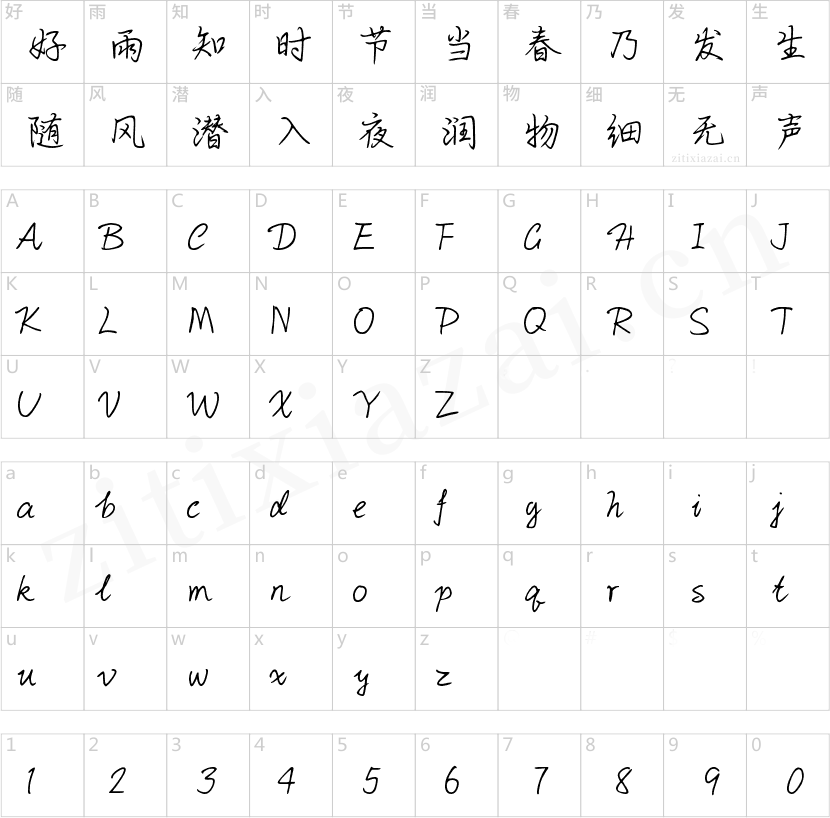
Aa做不到人人喜欢,这款字体结构工整、笔画清晰,兼顾美观与易读性,适用于标题、正文、海报、包装、LOGO 等多种场景。字形优雅稳定,风格百搭耐看,适配日常排版与创意设计,让文字呈现更舒适、更具质感。Aa做不到人人喜欢一笔一画,皆是细节,以均衡的比例、流畅的线条打造舒适视觉体验,字形端正大气,风格简约现代。无论是商业设计、品牌宣传还是日常排版,都能轻松驾驭,让文字更有格调与力量。Aa做不到人人喜欢字体下载。
Aa做不到人人喜欢是一款非常具有艺术性的字体,它的设计灵感来源于对古典艺术的研究,同时又融入了现代字体设计的元素。字形优美,笔画粗细变化自然,给人以大气、典雅的感觉。Aa做不到人人喜欢是一款既传统又现代的字体,它的设计充满艺术感,美观大方,实用性也非常强。无论是对于设计师还是对于普通读者来说,都是一种非常不错的字体选择。Aa做不到人人喜欢适合用于具有艺术感的场合,比如海报、宣传单张、书籍封面等。由于其字形流畅且具有动态感,也适合用于大量的文本排版,如报纸、杂志等。